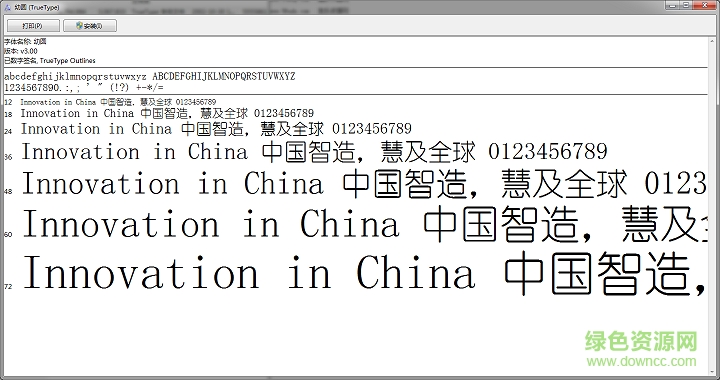
微軟幼圓體
微軟幼圓體是一款Windows系統(tǒng)必備的書法字體,有著圓潤(rùn)的轉(zhuǎn)角和秀氣的外觀,字體大方端正又不失活潑可愛,使用很廣泛,快來綠色資源網(wǎng)免費(fèi)下載吧!
微軟幼圓體介紹
微軟幼圓體是三星直裝字體,專為三星手機(jī)制作的微軟幼圓體字體,支持等寬,這個(gè)字體是最完美的,在linux上也很漂亮!
微軟幼圓字體
微軟幼圓體特色
在舊版本的幼圓體中,對(duì)舊字形的處理比較到位
拐彎處筆劃處理尤為細(xì)膩
筆劃更加細(xì)長(zhǎng),便于閱讀
微軟幼圓字體看起來有些像微軟雅黑,但比雅黑更纖細(xì)、轉(zhuǎn)角更圓、更顯女性化,相當(dāng)可愛!